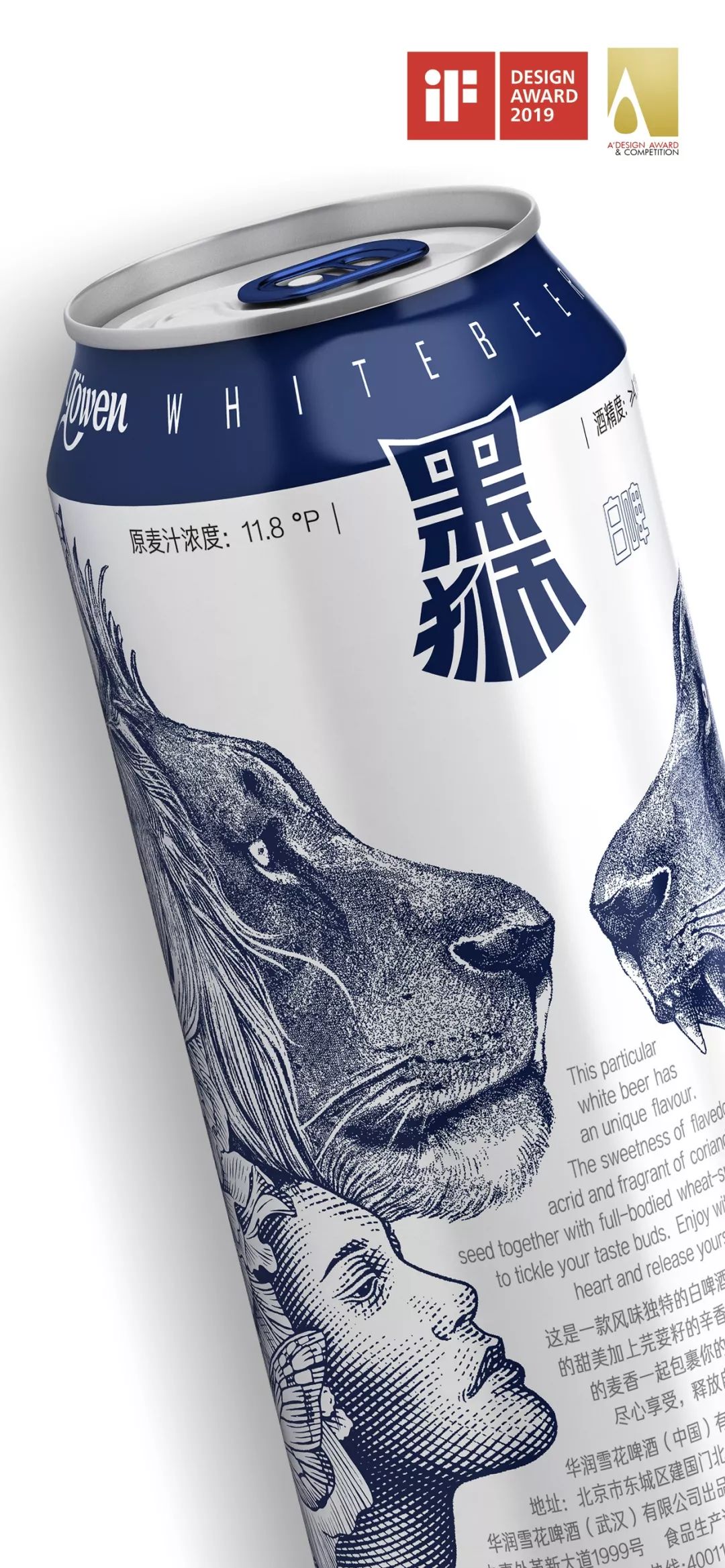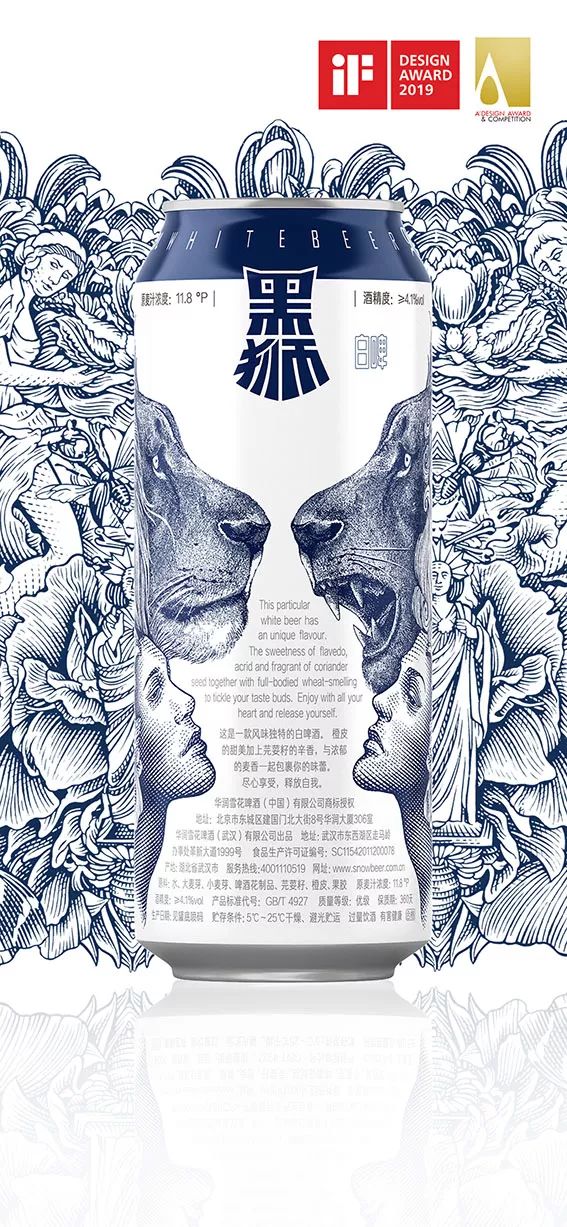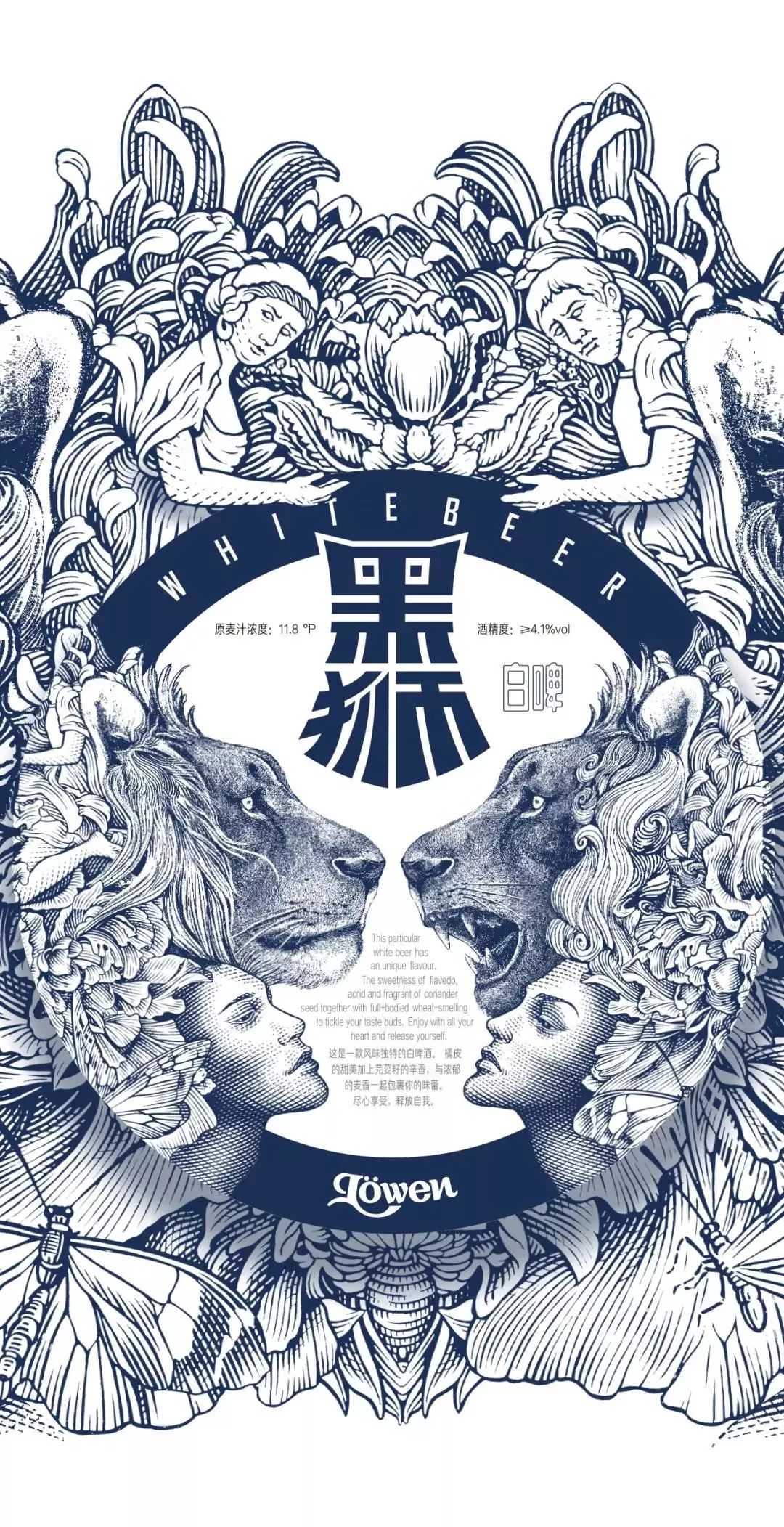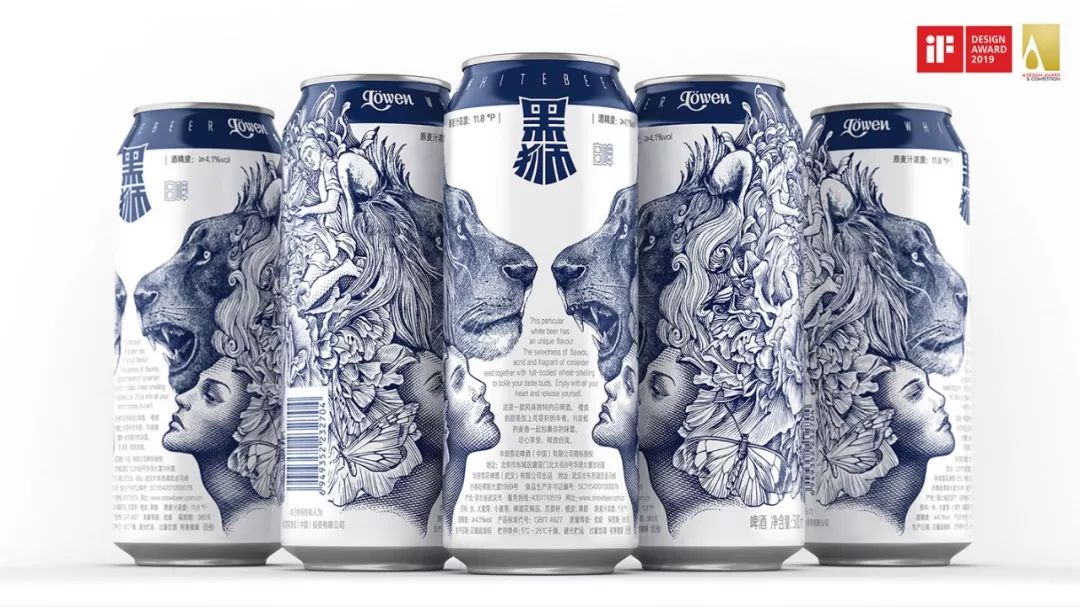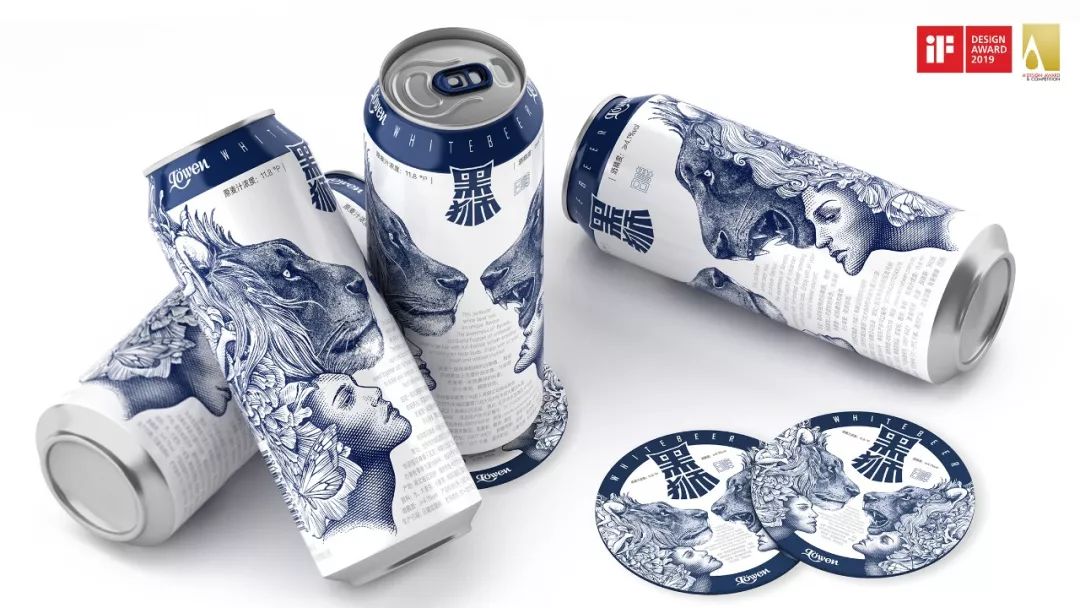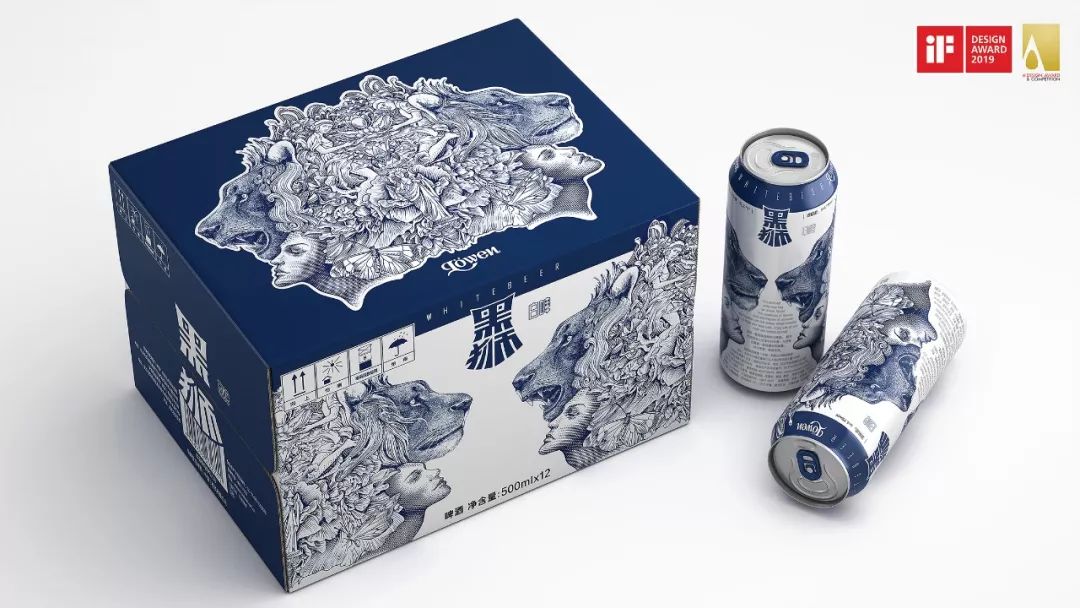
雪花白啤新包装,美女与野兽的设计很潘虎!
雪花·黑狮白啤出新包装了!
没错,又是由包装设计大咖-潘虎亲自操刀!
还有国际雕刻大师-马丁·莫克的倾情加盟
据大大君了解,这款产品在上市之前
包装已经获得2019德国iF设计奖
及2019意大利A设计金奖
还没上市,就获奖的包装设计?
我们一起来看一下——
黑狮啤酒是雪花啤酒旗下
全球销量第一的副线品牌
新包装的设计大改旧版的风格
变得更加设计感了!
首先是黑狮的字体上发生了很大的变化
“黑”字上方的“一”,两边进行了尖角处理
“狮”字采用了粗细不一样的笔画
两字结合呈现出一种张扬的感觉
总的来说,字体的设计
就是结合现代图形美学与品牌信息
进行了一种符号化升级
而与之搭配的包装设计
以靛蓝+纯白的经典搭配
简约时尚,视觉上给人带来舒适感
插画设计由钢笔画与铜版雕刻结合而成
以精致的线条,将两边人物的情绪细腻地描绘
呈现了一种对称之中的不对称之美
美女与野兽的组合
总能引起人们对杀戮以及爱情的无限遐想
结合线条的绘画和铜版雕刻
将狮子和人物的面部生动形象地呈现
两边的狮子传达情绪各不相同
一边是温和,另一边是狂野
两边对立,在视觉上带来了强烈的反差感
插画中的修道士身穿简陋的僧袍
身后开出了一大朵花
以此纪念繁盛时期的修道院啤酒
致敬传世经典、以及僧侣们对酿造的匠心
画上的蝴蝶带着西方古老的神谕和哲学体系
赋予黑狮神秘气息
整副插画的线条和人物比例处理得刚好
绘制功底可见一斑
字体和插画运用在包装上
风格相衬,搭配得刚刚好
包装盒沿用了靛蓝+纯白的颜色搭配
产品信息则为银白色,既不喧宾夺主
也给消费者带来了舒适的阅读感
不过,话说回来
潘虎和雪花已经不是第一次合作了
甚至可以说,雪花是潘虎的常年客户
像大大君之前跟大家介绍过的
清新凉爽系列
——雪花·马尔斯绿X潘虎
以马尔斯绿作为这款同名啤酒的主题色
从视觉色彩上提升雪花品牌的时尚感
同时为雪花马尔斯绿赋予冰爽的情绪感染力
并以极简化雪花矢量图
打造马尔斯绿的专属符号
还有致敬匠心系列
——雪花·匠心X潘虎
简化主品牌“雪花”为六边形超级符号
将副品牌名“匠心营造”以印章形式刻于六形棱中
呈现了一种中式之美
如果说,马尔斯绿代表的是感性美,眷恋而唯美
匠心营造代表的是知性美,闲适而高洁
那么,黑狮代表的便是野性美,肆意且洒脱